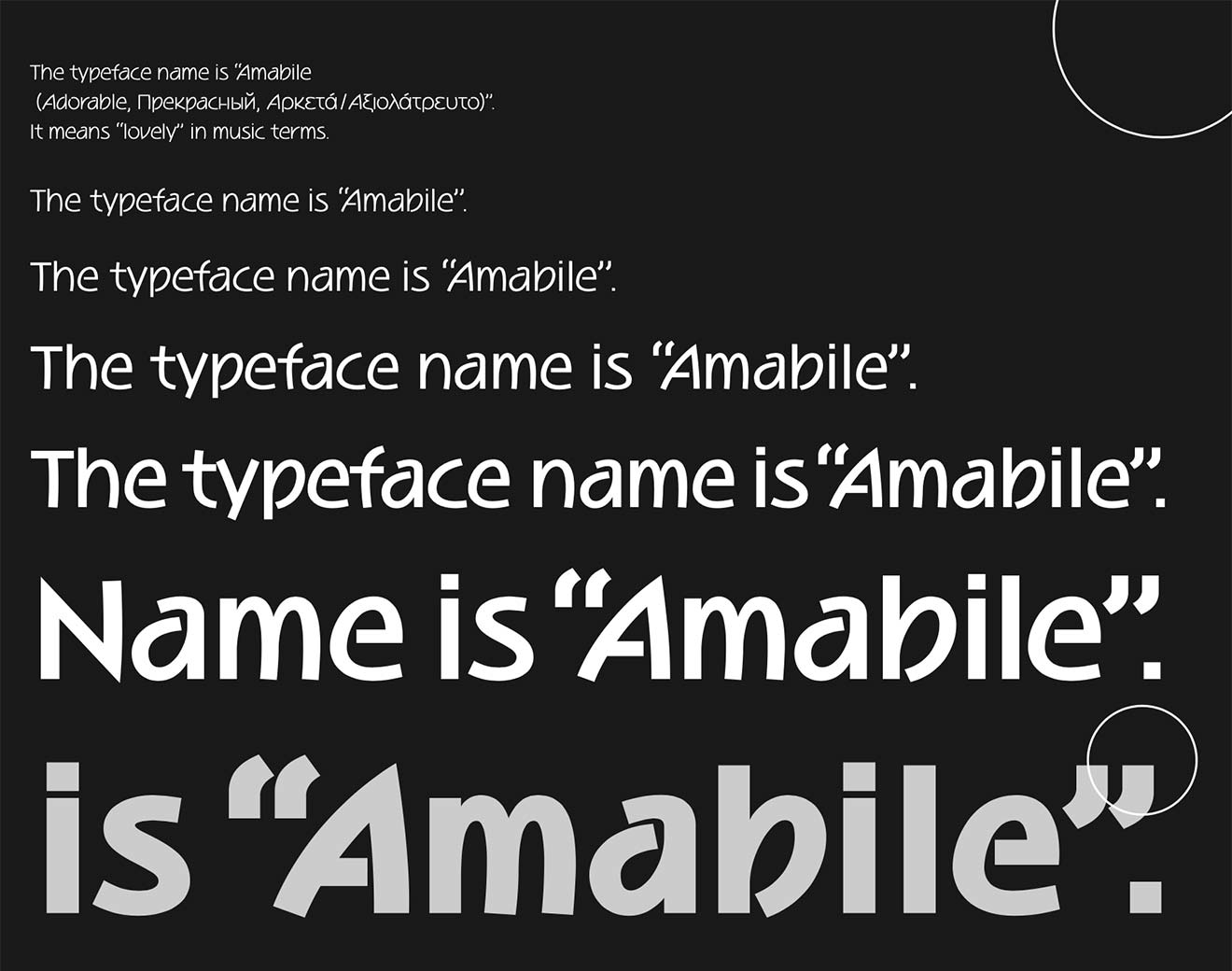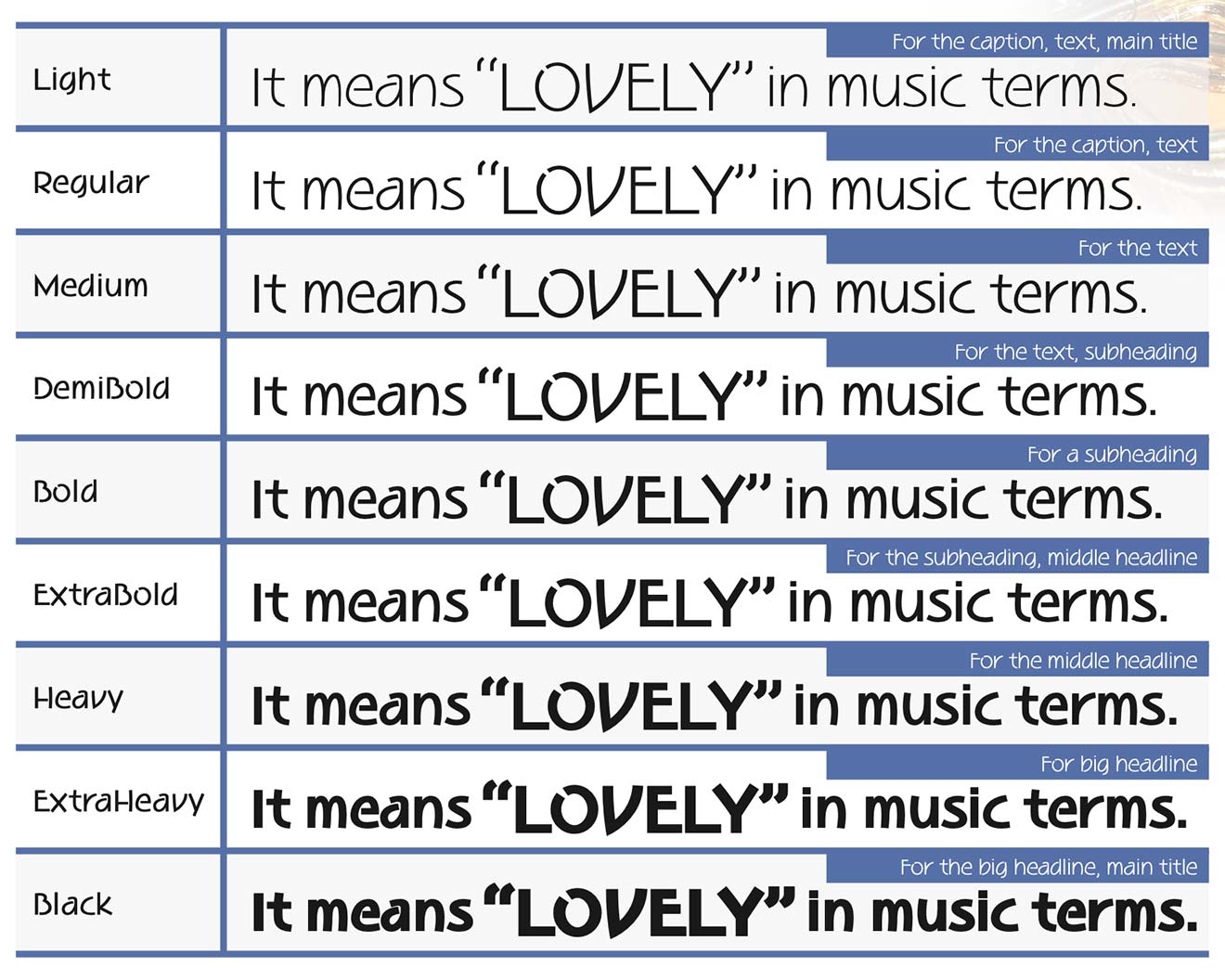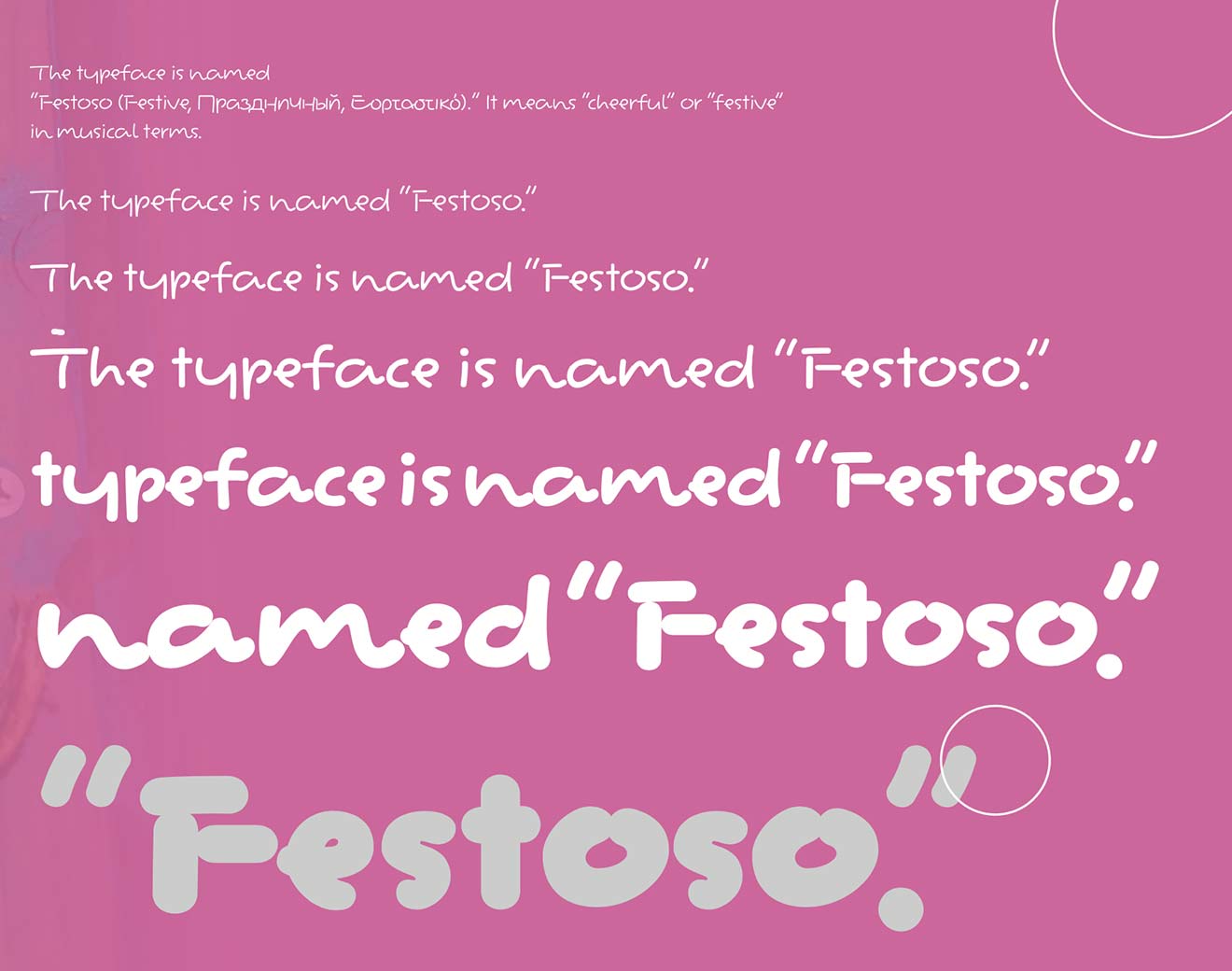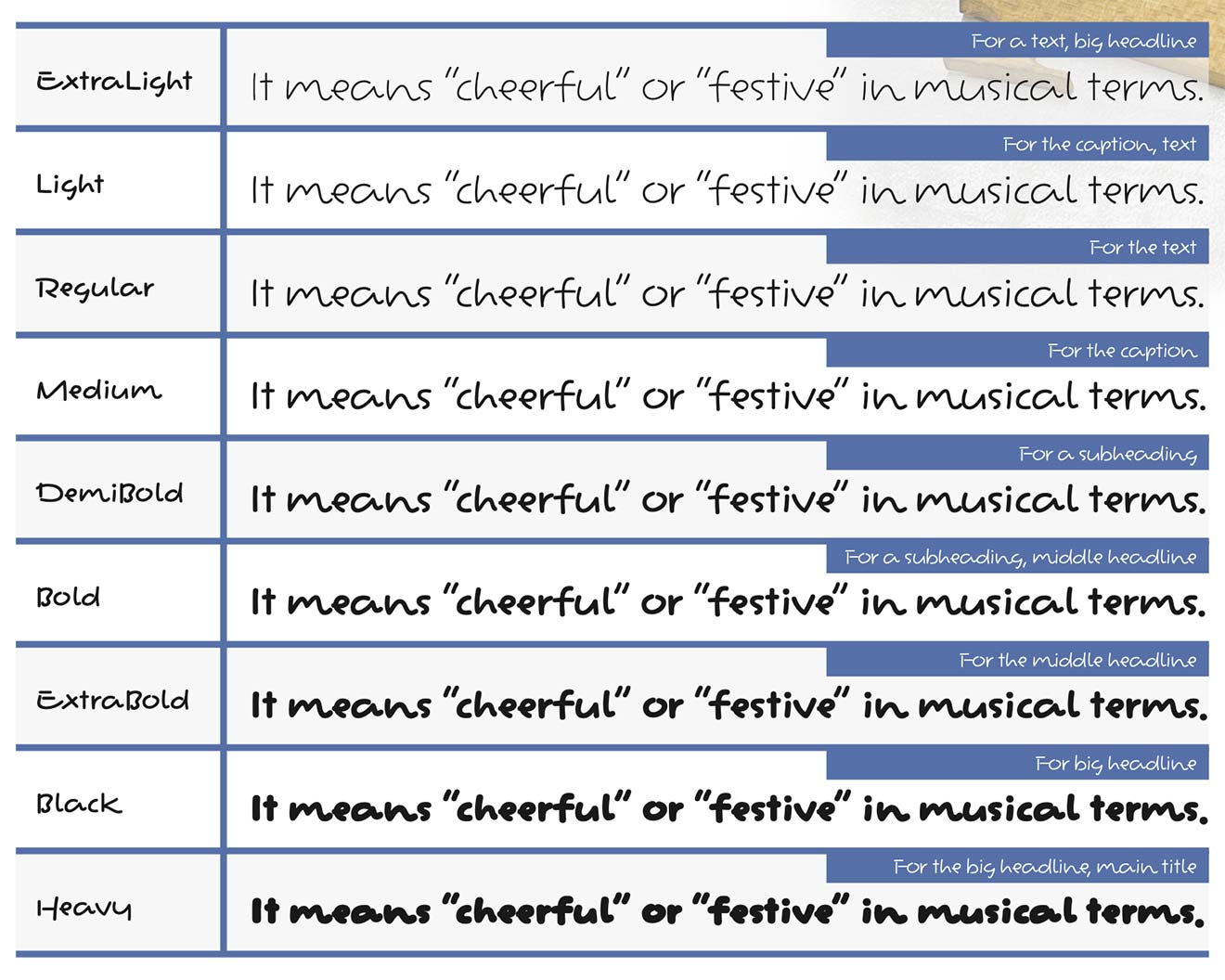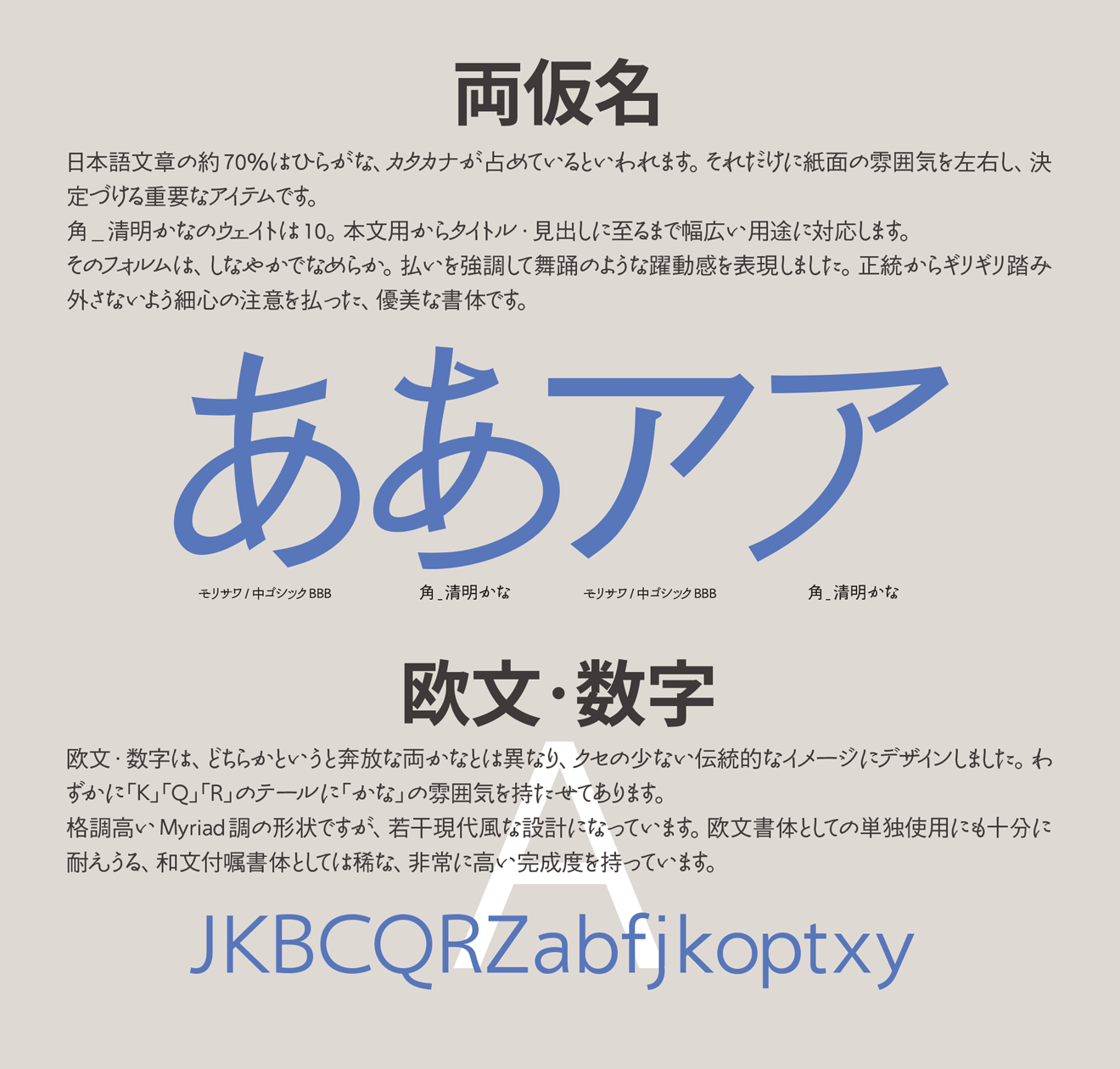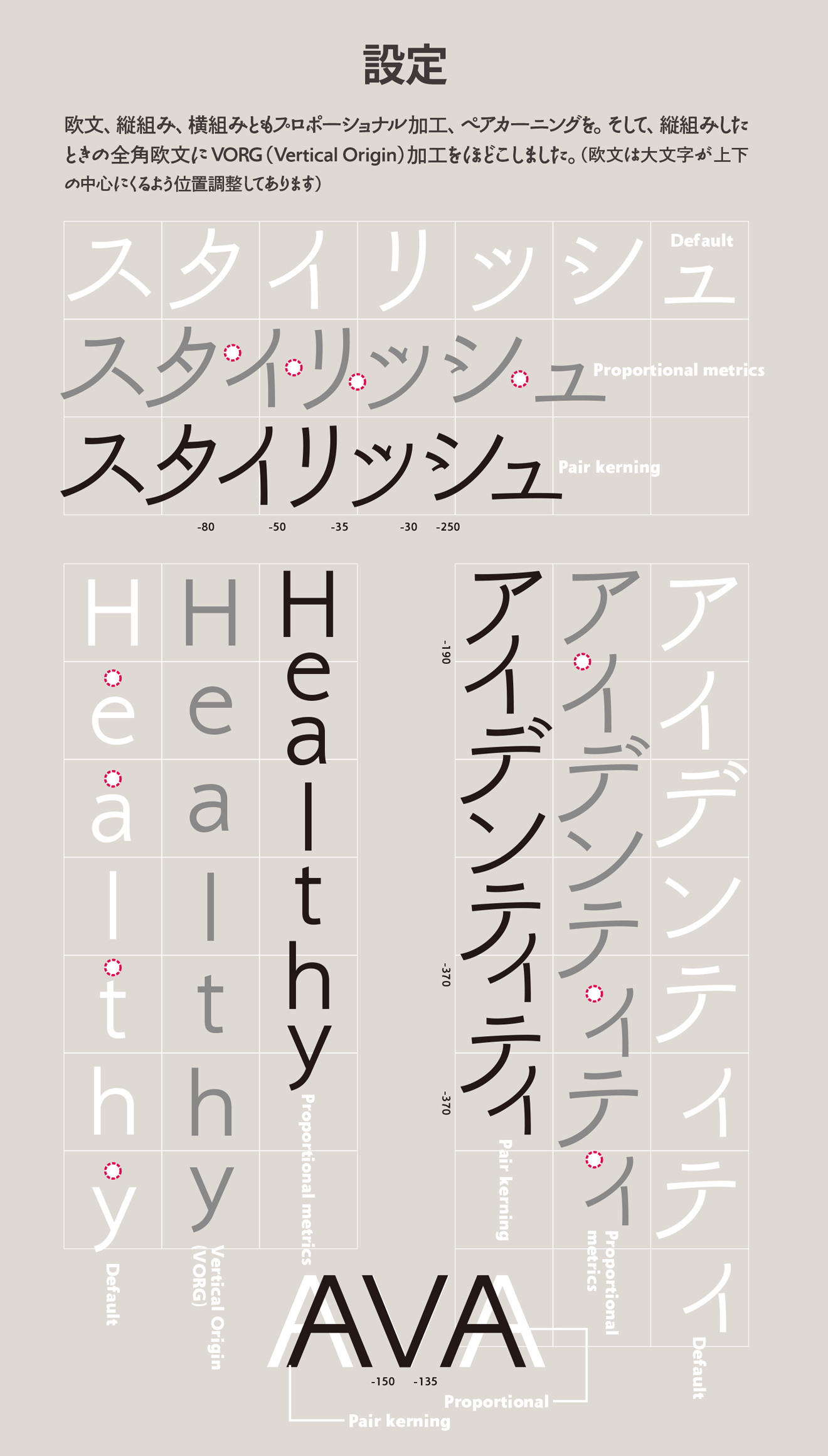
日本タイポグラフィ年鑑に入選を重ねる高評価ブランド「REN FONT」
日本タイポグラフィ協会主催の作品展「年鑑」のタイプフェイス部門で入選を重ね、着実に実績を積んできたREN FONT。タイプデザイナー・金井和夫が創り出すフォントはプロのデザイナーからも高い評価を得ています。
同協会「年鑑2001」で「勢蓮明朝M」初入選。「年鑑2003」で「松葉-Light」入選。「年鑑2004」で「奔行-Regular」入選。「年鑑2005」で「和音 9 Weights Family」入選と、3年連続4度の受賞。
そして、21年ぶりに出品した今年「年鑑2026」では「清明かな」「余韻かな」で5度目の入選を果たしました。
和音Pro (L/R/M/DB/B/EB/H/EH/U)
2005年度特定非営利活動法人日本タイポグラフィ協会により開催された「日本タイポグラフィ年鑑2005」コンテストの書体部門入選作「和音」を源流とし、制作されています。漢字、平仮名、片仮名、欧文、記号類、用途字種、数字の各字種のそれぞれに音楽的特徴をもたせ設計、それぞれがもつ特徴が見事に調和する、制作期間2年以上の全てを注ぎ込んだタイプデザイナー金井和夫渾身の労作です。
この書体は、最細ウェイト「L (ライト)」から最太ウェイト「U (ウルトラ)」に至るまで、合計9ウェイトを数学的アプローチで中間生成するという試みのもと、制作されたものです。
まさに「和音=ハーモニー」の名にふさわしい仕上がりとなっています。ぜひ、さまざまなシーンでご利用ください。
骨格の特徴
和音:漢字
ほとんどの文字のどこか1か所が切れて離れたデザインになっており、スタッカートのようなアクセント豊かな効果が生まれます。
また、終筆の跳ねをなくして緩やかな曲線にしました。これは、指揮者が振り下ろし振り上げるタクトの軌跡を表現しています。すべての文字に伸びやかさとおおらかさを与え、組まれた文章に音楽的な彩りや楽しさをもたらします。
和音:仮名
文章の約70パーセントを占めるといわれる仮名。作品の雰囲気を決める重要要素といって過言ではありません。
音楽に欠かせないリズムを表現するために、終筆をあえて中途半端な長さに終わらせて不安定にし、和音と相反する「不協和音」を表現し、動きを与えました。まるで音符のように機能し、オペレッタのような、可愛らしく軽やかなメロディが奏でられていきます。
和音:欧文
「和音」の基本コンセプトである「文字で音楽を表現する」を、最も端的に文字通りに「表現」しているのがこの従属欧文です。形状は、五線譜に踊る音符がモチーフになっています。とくに「d」「p」は四分音符そのものです。
サンセリフ書体は、一般的にエクスハイトが高めにデザインされています。それにより一文字ひともじが大きめになり、セリフ書体と比べて、現代的な雰囲気が強くなります。「和音」は、さらにエクスハイトを高めにし、大文字と小文字の差があまりありません。また、小文字のふところをより広めにデザインすることで、楽しさ愛らしさを表現しました。
集合体としての濃度ムラ
一文字一文字の美しさは言うまでもないことですが、組版を行ったとき (集合体) に濃度ムラがなく、均一であることは重要なデザイン要素。しかし、画数の極端に異なる漢字を並べた時、一定の濃度に保つことは至難の業です。
左の組見本はJIS第一水準漢字約3,000文字を和音Pro Lですき間なく敷き詰めたものですが、ほとんどムラがないのが特徴です。
制作段階では、この状態を実際に作りだして何10回も太さの微調整をくり返し、濃度のムラを最低限に抑えました。
他社仮名書体との共存を図る多ウェイト展開
和音は、デザイン書体でありながら極端にフォルムを崩さず、どちらかというと現代的ゴシック書体に近い形状になっています。また、デザイン書体には珍しい9つものウェイトを持っています。その多ウェイト化した理由のひとつに、既存の他社仮名書体との「共存」があります。
仮名フォントの中には優れたものが多く存在しますが、漢字がなくて不自由な思いをしているデザイナーさんもいらっしゃるはず。和音は個性を抑えている分、どんなウェイトの仮名フォントにも合う対応力をもっています。
これは、漢字の揃った総合書体と合成する「仮名書体の本来的役割」を、「漢字」に与えたまさに逆転の発想。もちろん、オリジナルの仮名部分にも絶対の自信をもっています。まさにオールマイティなデザイン書体なのです。
清流かな (L/R/M/DB/B)
究極の流麗さを追求した、明朝風と草書風のハイブリッドフォルム書体。
草書の走り書きの妙とも言うべき流麗さに、明朝の要素を加味して作り上げています。オールドなイメージを残しつつも、その概念にとらわれず大仮名に設計してあるので、近代的な組版にも対応するマルチな性格を備えています。
ボディの不揃いさはRENFONTの中でも最大級ですが、その分、心地よいゆらぎの効果は抜群です。その名のごとく清らかな水の流れのような、美しく味わい深い書体です。
はっぴかな (M/B/H)
明朝体とかすかに隷書の名残り、楽しさ溢れる愉快な文字。
法被(はっぴ)が上下左右に揺れるさまを表現。「ハッピー」にも係っています。
とにかく"まとも"な文字は一文字もありません。イメージは岸和田だんじり!?暴れまくっているので、動きのあるデザインには最適です。使いかたは、皆さん次第、適合する漢字も皆さん次第です。自由な発想を期待しています。
デザイン書体のかな文字はおしなべて形状が極端なので、普通のベタ組みではバランスがとりにくい傾向があります。「はっぴ」はまさにその極地。そこで「はっぴ」は、縦組み・横組みのすべての文字にペアカーニングをほどこしました。ですので、メトリクス処理をするだけで、バランスのとれた組みが得られます。
余韻かな (L/R/M/DB/B)
心地よい余韻を残してくれる味わい深い書体。
タイプデザイナー金井和夫の普段使いの文字をベースとした、明朝・行書の複雑なフォルムイメージを持っています。L (ライト)、R (レギュラー)、M (ミディアム)、DB (デミボールド)、B (ボールド) の合計5ウェイトで構成されています。
オールドなイメージを残しつつも、その概念にとらわれず大仮名に設計してあるので、近代的な組版にも対応するマルチな性格を備えています。特徴が強いので長文には向きませんが、短い本文組みや、ちょっとした見出しに使ってみてください。躍動感に満ちた、訴求力のある紙面になるはずです。縦組み、横組みともプロポーショナル加工を加えました。また、ペアカーニングも緻密にほどこしてあります。
ほんまるかな (EL/L/R/M/DB/B/EB/H/U)
伸びやかな切れ味の中に優しさ・優美さを包含した不思議な書体。
タイプデザイナー金井和夫の普段使いの文字をベースとしてデザインされたものです。やや左上に重心がある独特のフォルム。その危うさゆえに不思議なリズムを持っています。
丸ゴシックはもともとPOP寄りの柔らかなたたずまいをしており、デザイン書体との相性がよい書体。「ほんまる」は既存の他社丸ゴシックと組み合わせても違和感なく溶け込み、あたたかな雰囲気を醸し出します。
デザイン書体のかな文字はおしなべて形状が極端なので、普通のベタ組みではバランスがとりにくい傾向があります。そこで「ほんまる」は、縦組み・横組みのすべての文字にペアカーニングをほどこし、メトリクス処理をするだけでバランスのとれた組みが得られます。
ほんまるかなファミリーの各書体は、特徴が強いので、長文には向きませんが、短い本文組みや、ちょっとした見出しに使ってみてください。躍動感に満ちた、訴求力のある紙面になるはずです。
靜明朝小かな (L/R/M/DB/B)
小説などの長文に適した素直なフォルムの書体。縦書きに適した設計の「小かな」。
「小説などの長文を組んでもらいたい」とのコンセプトをもとに開発しました。読みやすさを重視しクセを極力なくしたフォルムになっており、特に縦組みに適しています。そのフォルムは、のびやかでなめらか。先端はすべて丸く処理しました。また、「か・な・ね」などの収筆は跳ねずに止めてあります。一文字ひともじの独立性を大切にしました。伝統書体を踏襲したフォルムですが、復刻版ではなく、現代にマッチするシャープな雰囲気も同時に持たせました。
縦組み、横組みともプロポーショナル加工を加えました。また、ペアカーニングも緻密にほどこしてあります。
音楽用語で「陽気な」「楽しい」といった意味をもちます。「ほんまるかな」の従属欧文として制作されたため、そのデザインには当然ながら「ほんまるかな」の持つ特徴が反映したデザイン。「ほんまるかな」の持つ遊び心や表情豊かさとの整合性を保つために、あえてスクリプト体(手書き風書体)でデザインしました。